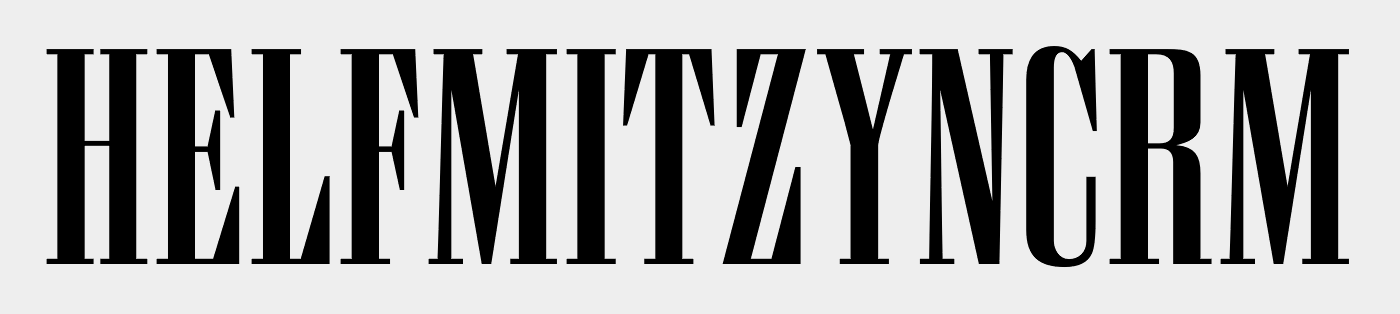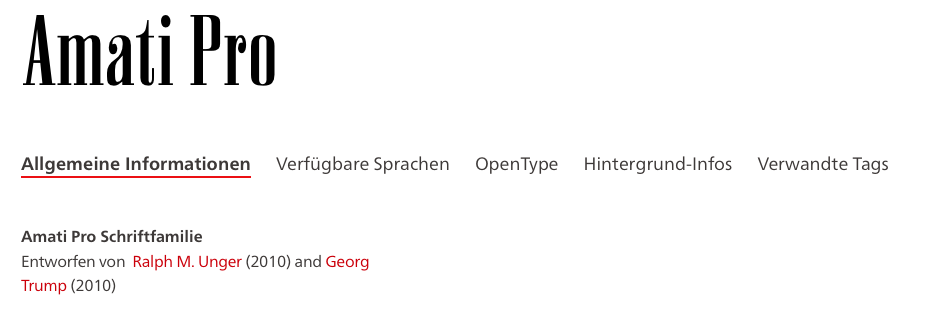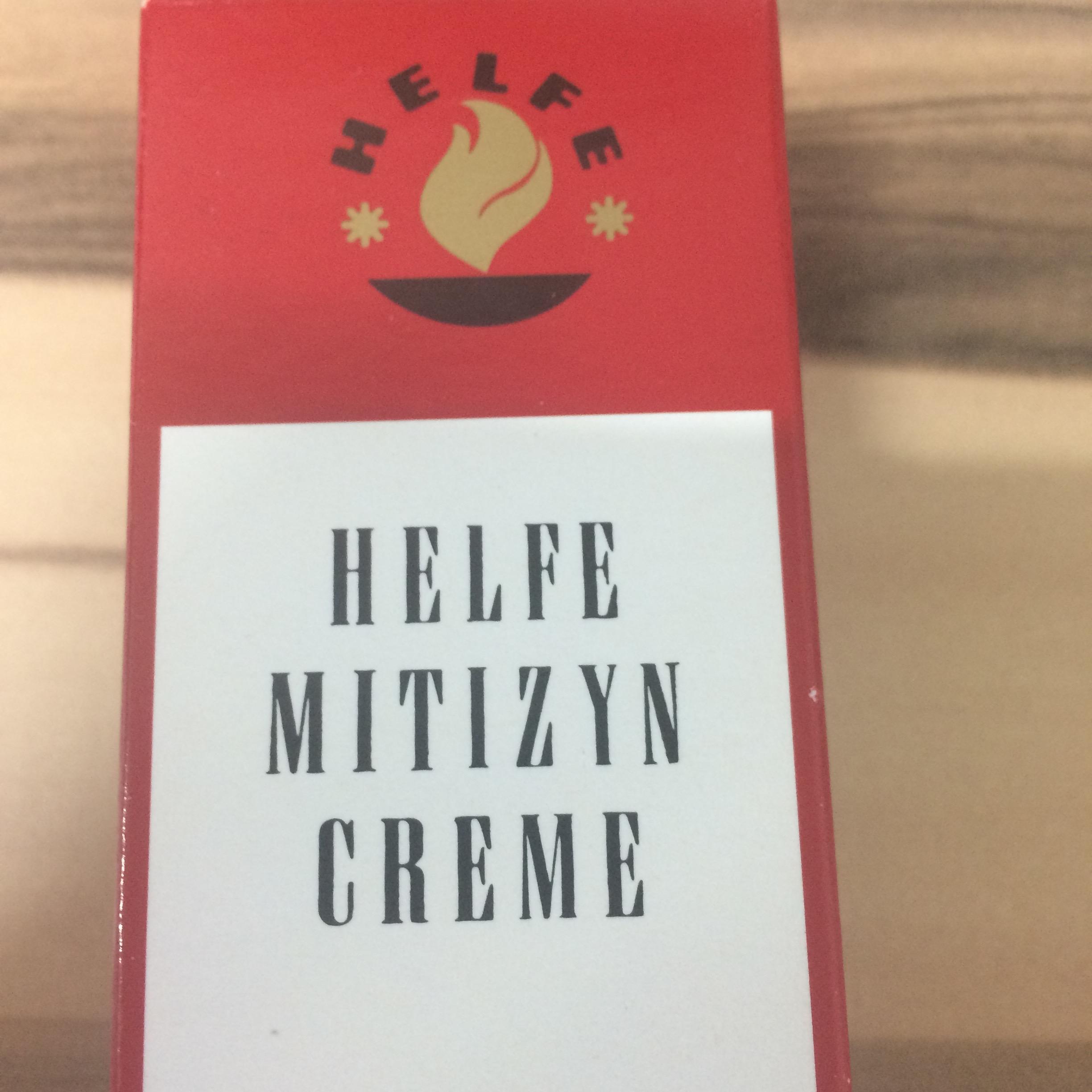
Ich habe eine Frage zur Lizenzverwendung. Für ein Produkt und dessen Verpackung verwenden wir seit ca. 30 Jahren die Schrift Amati Pro. Ich bin jetzt damit beauftragt worden dem Design ein Facelift zu geben, zwecks des Wiedererkennungswerts möchte ich auch weiterhin diese Schrift verwenden. Da das Design aber bereits so alt ist finde ich keine Lizenzen und auch nicht denjenigen der es erstellt hat.
Zu meiner Frage: Muss ich die Schrift Lizenz nur neu erwerben oder kann ich mich darauf berufen das dies Aufgrund der langen der Verwendungszeit (vor Zeiten der Internetpiraterie) bereits erworben wurde?
Wenn du eine Lizenz nachweisen kannst, brauchst du keine neue erwerben. Kannst du keine nachweisen, sind 34 € auszugeben wohl nicht zu viel verlangt … zumal eine neu gekaufte Schrift das @-Zeichen an Bord hat.
Ja, das schon. Aber ich wundere mich etwas, wie man seit 30 Jahren eine Lizenz für eine Schrift haben kann, die 2010 entworfen wurde und ein Pro im Namen trägt.
Ich vermutet sie verwenden die Schrift seit 30 Jahren, Quellen belegen das es die Schrift noch länger genutzt wird. Die Schrift selbst gibt es seit 1951.
Anscheind wurde diese damals von den Grafikern für die Verpackungen digitalisiert, was auch die etwas dicken Serifen auf dem Bild erklären würde. Schon deshalb würde ich die 34 Euro einmalig ausgeben und schon hat man was sauberes und legales in der Hand.
Mir ging es auch nur darum, dass, wenn eine Schrift namens Amati Pro verwendet wird, diese nicht seit 30 Jahren im Besitz sein kann – da es eben diese Digitalisierung noch nicht so lange gibt.
Ich würde auch dazu raten, eine neue Lizenz zu erwerben. Denn selbst, wenn die Schriftdatei 30 Jahre alt sein sollte, könnte man damit heute nicht mehr wirklich vernünftig arbeiten.
Alleine die Vorstellung, heute noch mit nur 256 Zeichen arbeiten zu müssen wäre mir ein Graus.
Das Design ist damals wahrscheinlich noch irgendwie ohne Computer erstellt worden. Zeichenmäßig ist es kein Problem da wir die Schrift nur genau für diese 3 Wörter brauchen.